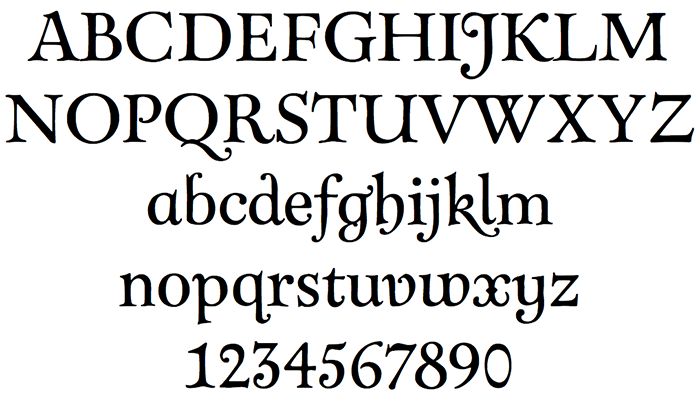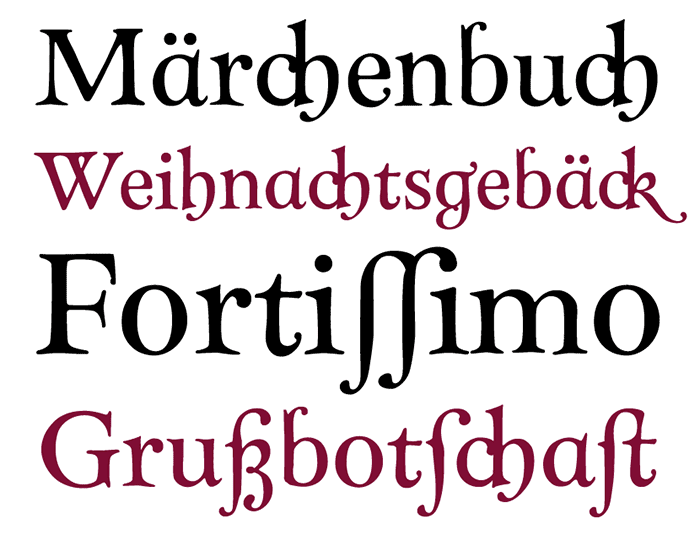
Die Abendschroth von Andreas Stötzner ist eine dekorative Antiqua mit verspielt-historischer Anmutung. Die Schrift ist in zwei Schnitten (normal und »scriptive«) mit 363 Glyphen verfügbar. Neben einigen typischen Ligaturen lateinischer Schriften enthält die Abendschroth auch Ligaturen für ch, ck, tz, ſſ und so weiter.
Ein Ableger der Schrift ist die Albyona English Nº 1, die zeitgleich erschien. Sie besitzt eine ähnliche Grundstruktur, besitzt jedoch deutlich rauere Umrisse und verzichtet auf die markanten Unterlängen und Tropfenserifen der Abendschroth.